Khám Phá Bộ Font Cute Hot Nhất Năm 2023
Việc tạo ra những thiết kế thu hút, hay đơn giản là chia sẻ một status ấn tượng trên Facebook , đòi hỏi bạn phải có những công cụ hỗ trợ đắc lực.
Trong đó, việc chỉnh sửa ảnh với những font chữ đẹp mắt đóng vai trò vô cùng quan trọng.
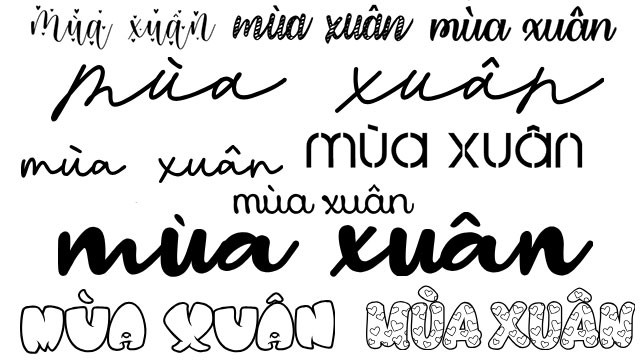
Ưu Điểm Vượt Trội Của Bộ Font Cute
Bộ sưu tập này bao gồm hơn 40 font chữ được thiết kế theo phong cách dễ thương, phù hợp với nhiều mục đích sử dụng khác nhau.
Từ việc tạo tiêu đề, viết chữ trên ảnh, đến thiết kế poster, banner quảng cáo, tất cả đều trở nên sinh động và bắt mắt hơn nhờ sự góp mặt của những font chữ này.
Bộ Font Cute – Phiên Bản Cập Nhật 2023
Bộ sưu tập này quy tụ hơn 40 phông chữ được lựa chọn kỹ lưỡng, đáp ứng các tiêu chí về sự trẻ trung, phong cách thời trang và nét dễ thương đặc trưng. Trong khi Bộ Font Full cung cấp một tổng hợp toàn diện các phông chữ cơ bản, hữu ích trong thiết kế và soạn thảo văn bản , thì bộ font này tập trung vào những kiểu chữ mang tính hiện đại, tạo ấn tượng thị giác mạnh mẽ cho người nhìn ngay từ lần đầu.
Từ thiết kế đồ họa, xây dựng website, đến chia sẻ nội dung trên mạng xã hội, chèn chữ vào ảnh hay video, bộ font này đều đáp ứng tốt.